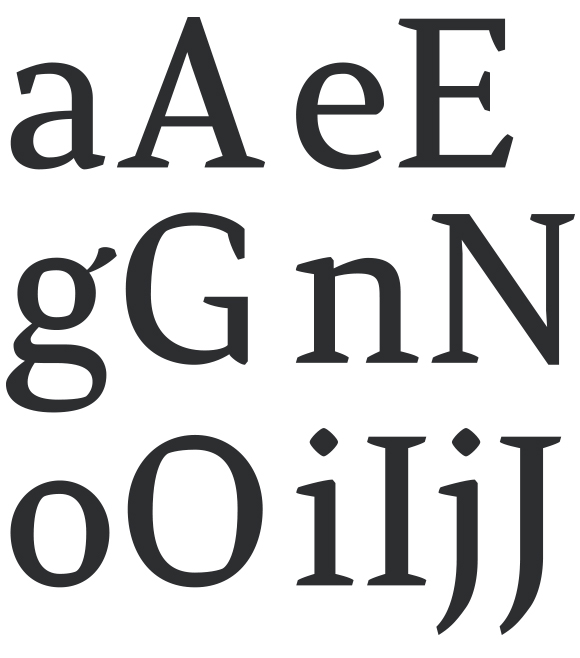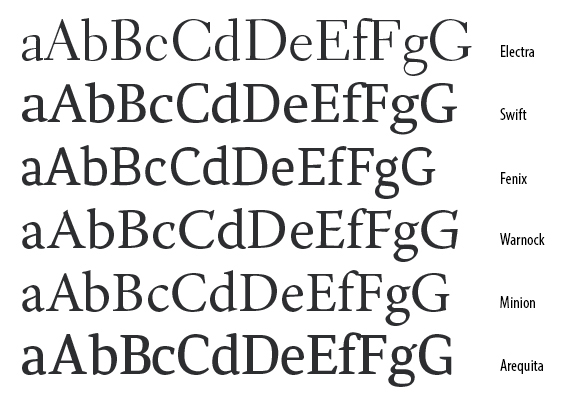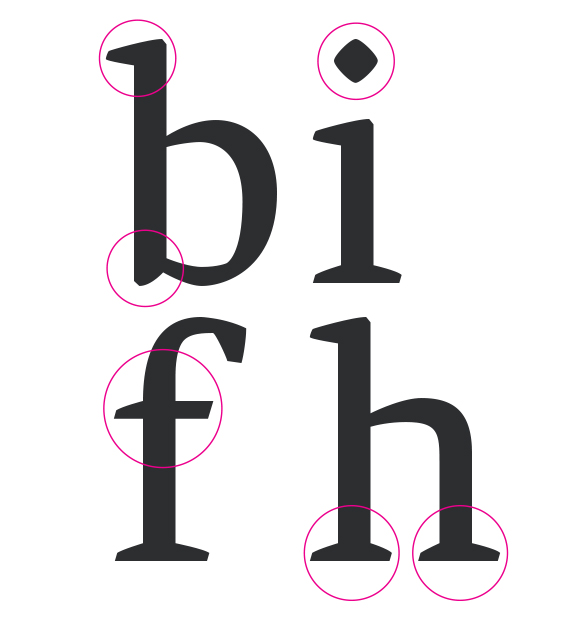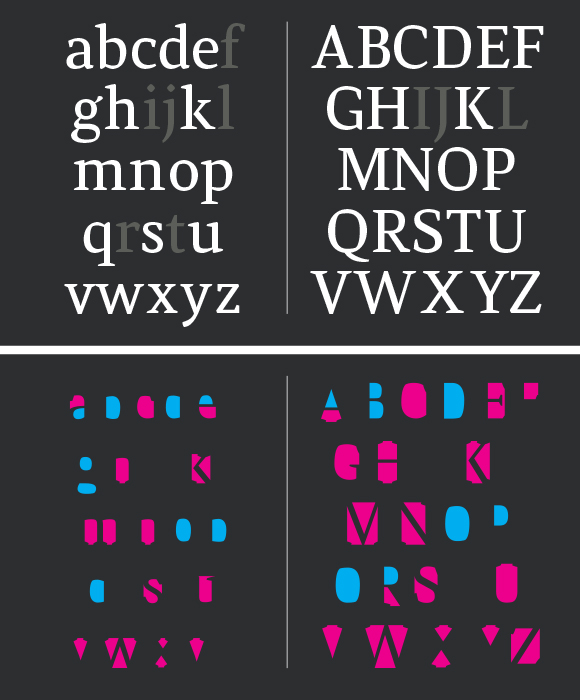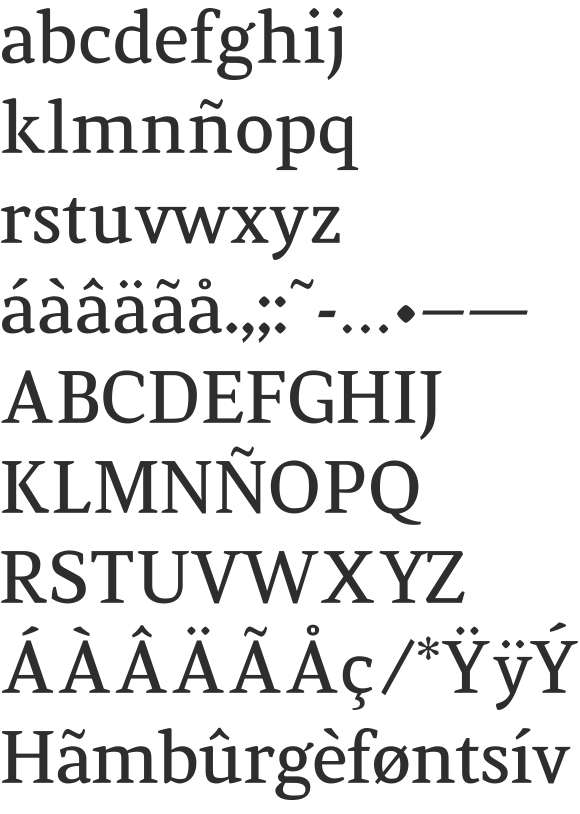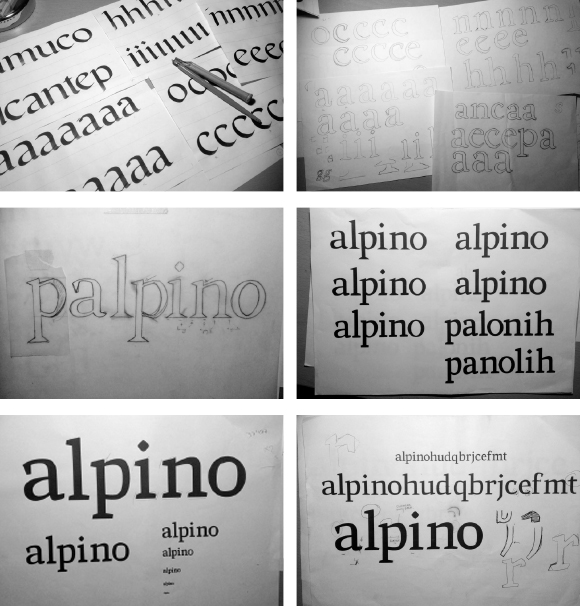
Este año hemos celebrado el primer curso de diseño de tipografía Unostiposduros-Familia Plómez. Una maravillosa experiencia que disfrutamos junto a trece alumnos y que el próximo año confiamos en volver a repetir. En este artículo uno de ellos, Pablo Tellechea, nos relata la génesis de su proyecto, una tipografía de texto a la que ha puesto el nombre de Arequita.
Arequita es una tipografía con remates para texto impreso. Está pensada para procesos de lectura prolongada y para ser reproducida en cuerpos de texto relativamente pequeños, de entre 8 y 14 puntos. Es una tipografía para leer, no para observar. Su construcción se ha inspirado en tipografías que se rigen bajo la fórmula-M.
Mi mayor motivación ha sido diseñar una tipografía como excusa para aprender algo más sobre la materia y no tanto para convertirme en un diseñador tipográfico. Estoy muy lejos de serlo.
Preliminares
Diseñar una tipografía para texto carece de la originalidad y la libertad creativa de la que podrían disponer otros proyectos, como las tipografías para titulares. La tradición de cientos de años pesa tanto que el margen de maniobra es limitado. Arequita es, por tanto, una interpretación más de los rasgos que definen las formas solidificadas del alfabeto latino. En una sociedad en la que se premia la originalidad y se admira la novedad, esto puede llevar a una crítica fácil. Pero, en el diseño de tipografías para texto, una excentricidad desmesurada puede generar resultados interesantes pero poco funcionales.
Me gustaría afirmar que Arequita no es fruto de la improvisación. Que la tenía en la cabeza desde hacía tiempo y que fui madurando su estructura. Pero no es así. Sabía que quería una tipo de texto con remates y poco más. No me había imaginado nada en concreto, las ideas eran vagas y el concepto excesivamente generalista.
Después de dibujar los primeros caracteres a lápiz, los tracé en Illustrator. Comencé a familiarizarme con la metodología y la lógica formal en la que iba a basarse mi tipo. Días después me sumergí en el «apasionante» mundo del FontLab.
Referencias formales y referencias métricas
Me interesaba trabajar las ideas que definen la fórmula-M, un método concebido en 1937 por William Dwiggins. Aunque el término fórmula está bien empleado, puede llevar a la falsa idea de que se trata de una ecuación mágica para obtener una serie de parámetros esclarecedores. En realidad, es una técnica que queda abierta a la libre interpretación por parte de quien quiera emplearla. Los resultados pueden variar bastante. En algunos casos las formas que resultan muestran un aspecto curioso. Por ejemplo, si aislamos la letra g de Andralis, de Rubén Fontana, es probable que nos parezca tan extraña como fea. Pero, integrada en una composición, ese déficit estético deja paso a un sistema compacto, lógico y funcional.
La fórmula-M consiste en engañar al ojo haciéndole ver curvas que no existen. Eso se consigue acentuando las características más distintivas de los caracteres con trazos muy marcados y angulosos. Dwiggins fue el primero en aplicar esta lógica en un proyecto experimental y más adelante en su tipografía Caledonia. Su objetivo era dar viveza y definición a las fuentes de cuerpos más pequeños.
Es curioso cómo Dwiggins llegó a la fórmula-M. En 1930 comenzó a colaborar con un grupo de teatro que tenía un espectáculo de marionetas. Él era el encargado de pintar las caras. Comenzó con un estilo muy definido, muy realista, pero la distancia a la que se encontraba el público y la iluminación de la sala, contribuían a que esos detalles se perdiesen y no causaran el efecto esperado. Fue entonces cuando pensó que ganaría vivacidad si simplificaba los rasgos de los rostros. Al hacerlo, la distancia y la luz se aliaban y, como resultado, la percepción de los espectadores mejoraba ostensiblemente. También las curvas y las líneas podían combinarse para obtener mayor dinamismo.
Dwiggins entendió que su descubrimiento podía aplicarse al diseño tipográfico. Bautizó su método como fórmula-M, donde la M respondía a la inicial de marioneta (marionette, en inglés). La idea clave de la fórmula-M, lo que me atrae tanto de ella, es su énfasis en engañar al ojo: dar a la mentira apariencia de verdad, provocar una ilusión, inducir a tomar por cierto lo que no es… Algo tal vez criticable pero que en tipografía solo persigue un objetivo: mejorar la lectura y, por ende, la comunicación. Entre las tipografías que aplican esta técnica y que he tomado como referencia me gustaría destacar Electra, de Dwiggins; Swift, de Gerard Urger, y Fenix, de Fernando Díaz. Otras tipografías que, aun sin responder a la lógica de la fórmula-M, he tenido en cuenta en la definición de algunos detalles son Warnock y Minion, ambas de Robert Slimbach.
Una vez perfilados los parámetros de las primeras letras, es momento de determinar las distintas líneas de referencia.
Arequita, al estar pensada para reproducirse en cuerpos pequeños debía contar con un generoso ojo medio; es decir, el espacio que engloba la línea base y la altura x. El ojo medio es el área que más información aporta de una tipografía. Dependiendo de las relaciones que guarde el ojo medio con el resto de las líneas de referencia, percibiremos un mismo texto más grande o más pequeño, por más que esté definido con el mismo cuerpo.
Llegados a este punto, los no expertos deberán realizar un acto de fe cuando afirmo que Arequita cuenta con un ojo medio grande. Es grande, pero… ¿con respecto a qué? Con respecto a las proporciones de otras tipografías con remate susceptibles de ser empleadas en el mismo proyecto editorial.
El siguiente gráfico muestra los porcentajes de las áreas que se establecen entre las líneas de referencia de ocho tipografías con diferentes características, reproducidas a un mismo cuerpo. Carece del rigor suficiente para demostrar que Arequita cuenta con un ojo medio generoso. Para eso deberíamos mostrar un número muy superior de fuentes.
Para terminar, más allá del acierto o desacierto formal de Arequita, destaco el proceso de trabajo. Un proceso díscolo y un camino vacilante que transcurre entre los márgenes del entusiasmo y la desesperación. No ha sido fácil, pero ha sido sumamente enriquecedor y divertido. Bienvenidas sean las excusas.